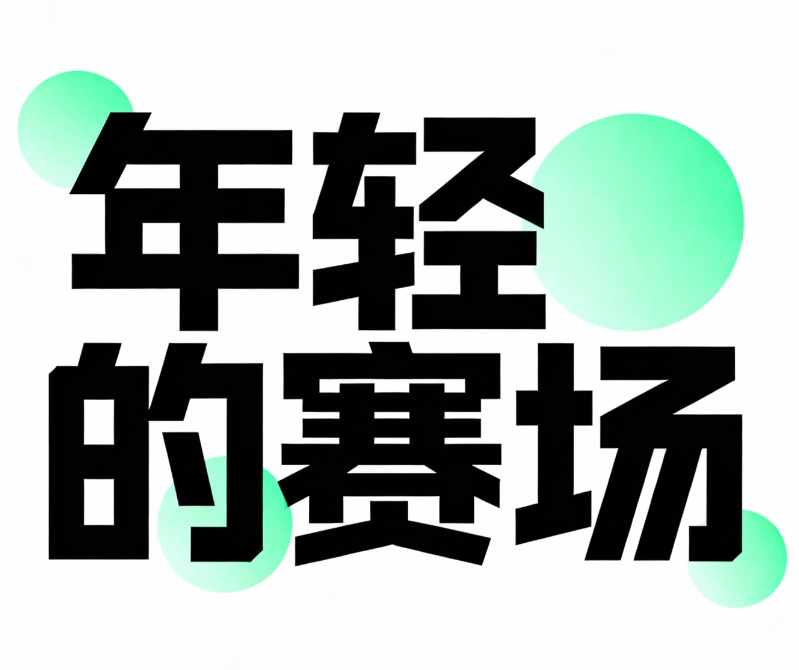
平面设计风格艺术字体设计,“年轻的赛场” 中文字...
平面设计风格艺术字体设计,“年轻的赛场” 中文字...AI字体提示词
风格定位
适合做风格探索与字形灵感延展。
适合场景
海报设计、品牌标题、电商设计、创意视觉
平面设计风格艺术字体设计,“年轻的赛场” 中文字样采用几何化、现代无衬线字体,笔画方正且富有块面设计感,以纯黑为主色调,整体排版活泼有层次。画面融入清新浅绿色圆形装饰元素,背景为纯净白色,营造出年轻、活力、充满竞技感的视觉氛围,细节上体现字体的几何结构张力与色彩的明快对比,适合用作年轻向竞技活动的标题字体设计,风格现代简约且富有设计感。
可替换关键词
金属纸张肌理浮雕高对比立体阴影强笔触“年轻的赛场”现代无衬线字体以纯黑为主色调背景为纯净白色
生成建议
• 先保留核心风格词,再替换材质、颜色和光影词做多轮尝试。
• 如果用于品牌标题字,补充品牌气质、行业属性和情绪关键词。
• 如果用于海报或电商标题,额外强调大字、对比度和视觉冲击力。